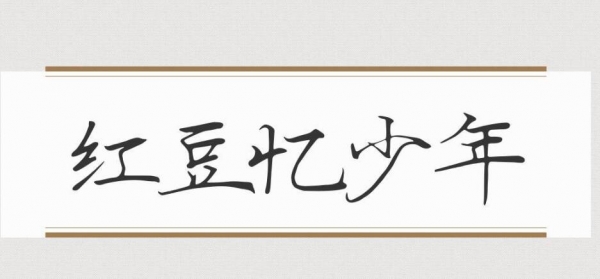
紅豆憶少年是一款非常不錯(cuò)的手寫字體,個(gè)性醒目,具有強(qiáng)烈的視覺沖擊力,適應(yīng)于報(bào)紙和雜志和書籍中常用字體, 海報(bào)、個(gè)性促進(jìn)品牌標(biāo)志設(shè)計(jì)、字體設(shè)計(jì)、等環(huán)境使用,歡迎喜歡的朋友前來(lái)下載使用。